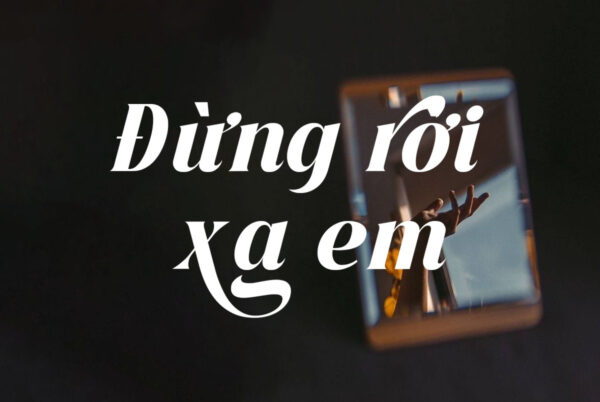
Font Việt Hóa MJ Monalisa – Sang Trọng & Thanh Lịch
MJ Monalisa là một font chữ hiện đại, mang phong cách thanh lịch và mềm mại, phù hợp cho thiết kế logo, poster, thiệp mời, tiêu đề và nhiều ứng dụng sáng tạo khác.
Đặc điểm nổi bật:
✅ Việt hóa hoàn chỉnh – Hỗ trợ đầy đủ dấu tiếng Việt, giữ nguyên nét đẹp nguyên bản.
✅ Đường nét tinh tế – Chữ mềm mại, uốn lượn nhẹ nhàng, tạo cảm giác sang trọng.
✅ Ứng dụng đa dạng – Phù hợp cho branding, typography, thiết kế in ấn và digital.